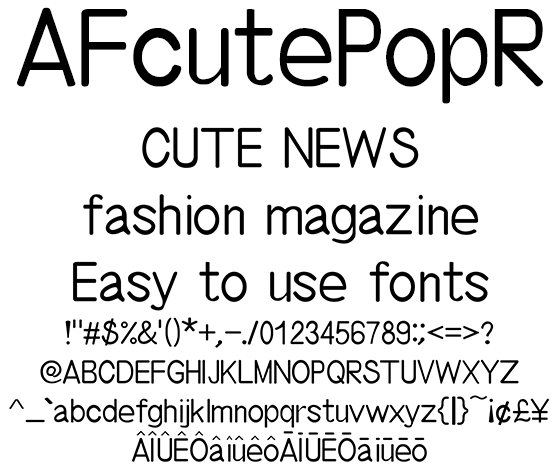
キュートな丸ゴシック欧文フォント AFcutePopR
AFcutePopR
とにかく目立つ丸ゴシックなレギュラーウエイト欧文フォントは、キャッチな場面の同人系、コミック、アニメ、ゲームに最適。パンフレット、リーフレット、フライヤー、ファッション系コンテンツに使えるフォントです。日本のローマ字表記で使われる訓令式やヘボン式で扱う Ô や Ō を収録、人名地名へのアプローチもリアルです。